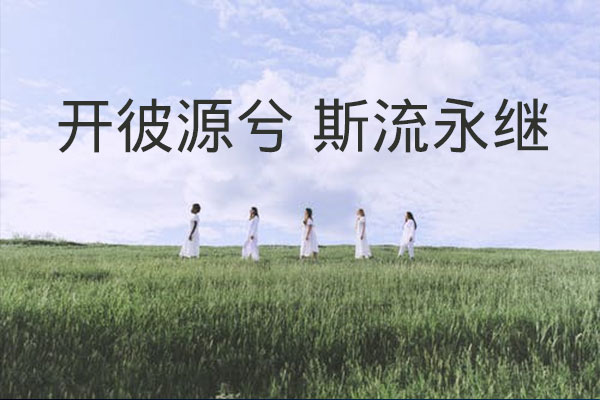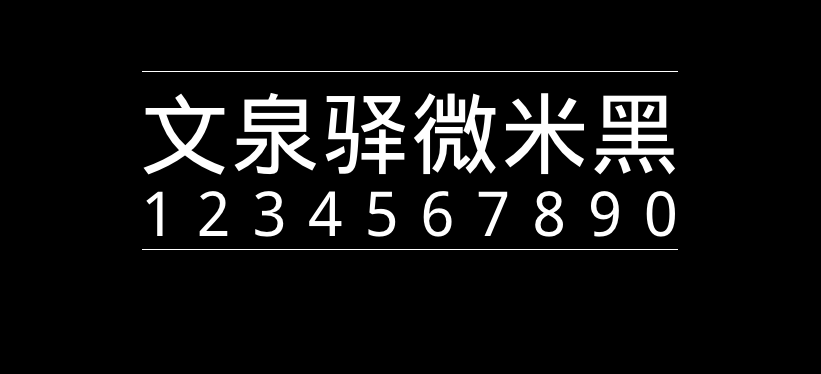
文泉驿微米黑
文泉驿微米黑(WenQuanYi Micro Hei)来自学者房骞骞2004年发起的公益项目——文泉驿;文泉驿微米黑是一个”自由字体”。该字体包含了所有常用简体中文、繁体中文所需要的汉字(最新版本包含超过20932个汉字,完整覆盖GB2312/Big5以及GBK标准字符集)。该字体同时还包含了日文、韩文和其他几十种语言符号。以外,该字体还包含了高质量的Droid Sans拉丁符号和Droid Sans Mono等宽字体,并内置Hinting和Kerning信息。微米黑字体文件极小,特别使用于便携式电脑设备。
该字体包含粗细两个版本:等宽微米黑,细微米黑。
说到中文字体开源的鼻祖,学者房骞骞2004年发起的公益项目文泉驿应该算一个,开源、允许商业发布。据说发起这个项目,初衷是改善当时高质量中文字体匮乏的情形,以适应Linux系统开发。字体不多,但支持的字很全。可惜很早之前已经停止更新,也没有更多新的免费字体。确实要维护公益性项目实在是困难重重。